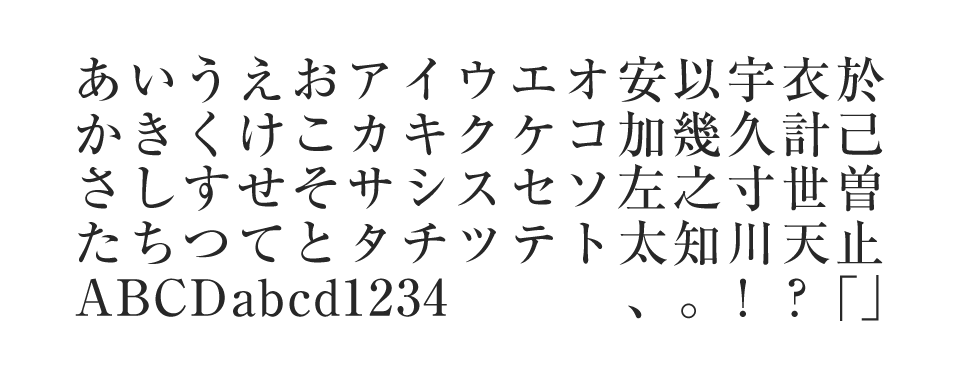
string(570) "「リュウミン」は、その名の元となった森川龍文堂明朝体をベースに開発した、スタンダードな明朝体です。金属活字に由来する彫刻刀の冴えを、左右のハライや点の形に活かしながらも、縦画・横画の先端やウロコにはやわらかさをもたせており、親しみやすい雰囲気になっています。特に、均整のとれた流れるような表情の美しさには定評があり、本文組みから見出しまでDTPの基本書体として幅広く使用されています。"
string(406) "遊び心のある脱力系のゆるい書体です。ひと文字がそれぞれ不安定かつユニークなデザインで、手描き風書体のもつ《あたたかい》《やさしい》《素朴》を表現するのに最適で、さらには極太ウエイトならではの《柔らか》《ほがらか》な表情をもつ書体です。</p> "
string(474) "美しい打ち込みや伸びやかなハネ、ハライが特徴的な、筑紫書体のオールドスタイルの明朝体です。<br /> 2008年にリリースした【筑紫オールド明朝】の一部の漢字のデザインをさらに伸びやかにリデザインし、書体名も新たに6ウエイトのファミリーを揃えました。狭いふところのデザインにより、文字が図形的ではなく文字らしく見えてきます。"